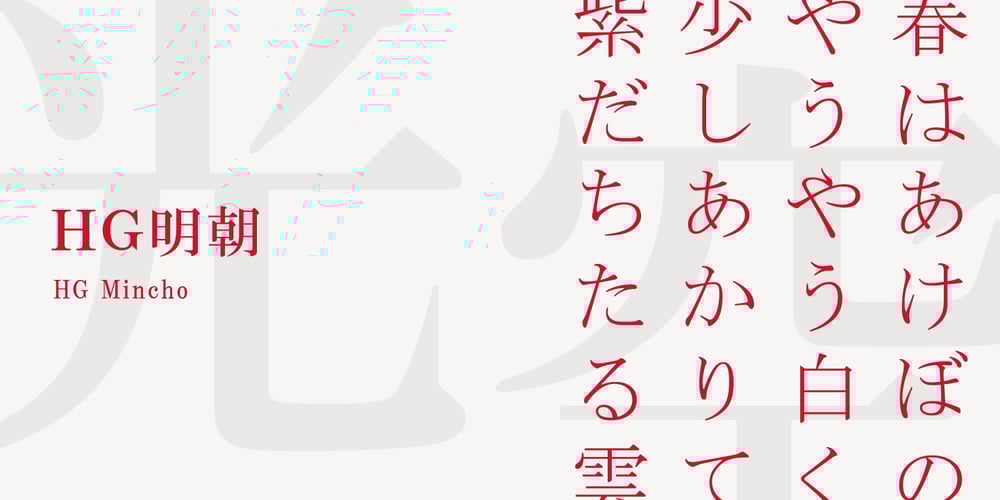
HG Mincho Font Family was designed by published by RICOH. HG Mincho contains 3 styles and family package options. HG明朝は、リョービの「本明朝」を字母とする明朝体です。現代的なイメージにするため、仮名文字の一部は変更されています。クラシックでシャープな書体ですが、ふところは大きく、読みやすい書体です。縦、横線の始筆部のふくらみをカットすることで、初期のPCディスプレイでの表示品位向上を実現しています。また、線幅補正ヒンティングのため、線幅の種類を抑制しています。HG明朝Lは、MS明朝と同じデザインです。